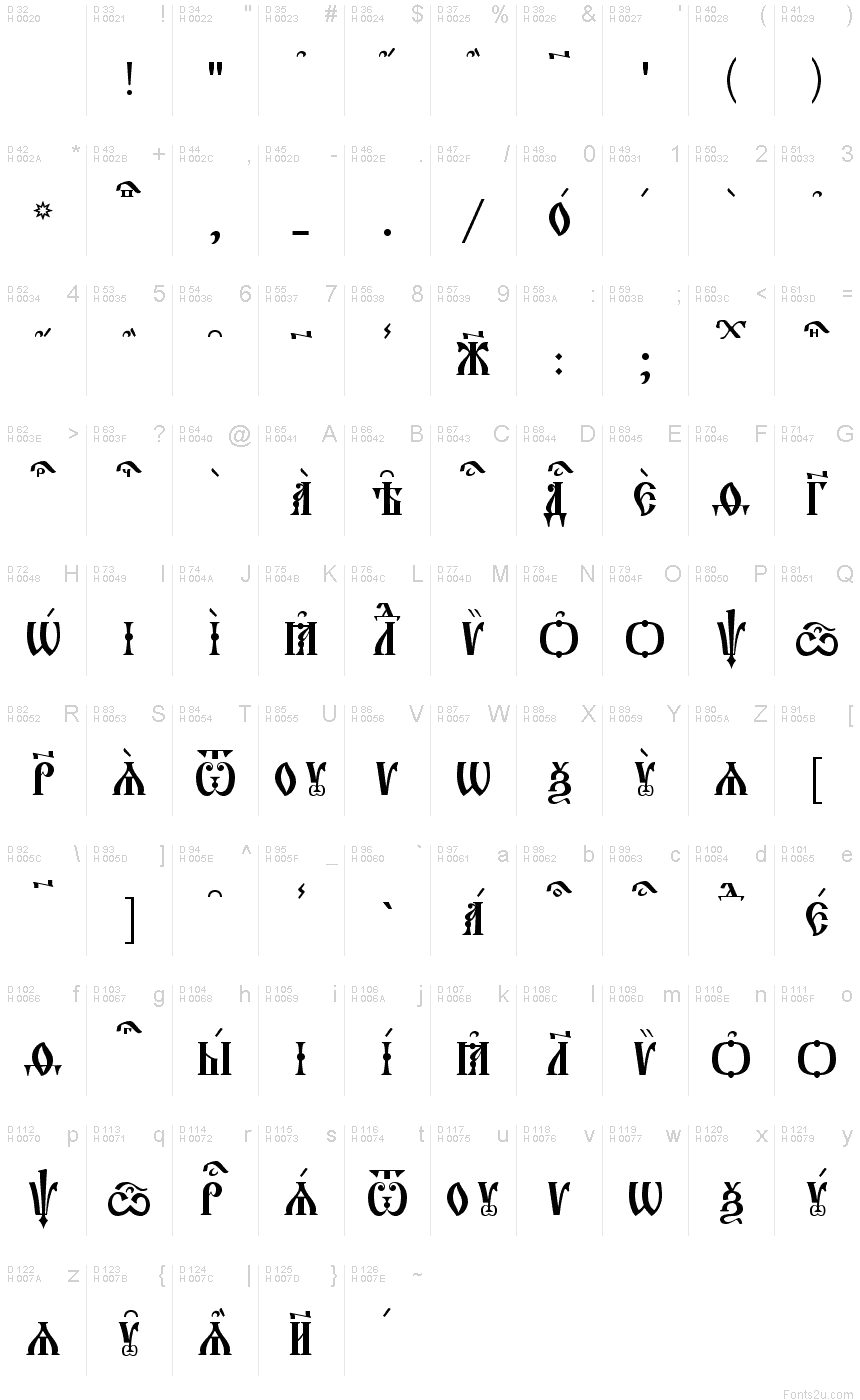
Orthodox TT UCS8 Caps SpacedOut, creata da SoftUnion Ltd e N. Andrushchenko, è un font cirillico gratuito in maiuscolo che richiama lo stile delle iscrizioni ecclesiastiche e delle antiche pagine liturgiche. Le lettere uniscono silhouette ampie e cerimoniali a piccoli dettagli a goccia, riccioli interni e accenti a forma di croce, rendendo il carattere solenne ma al contempo decorativo.
È perfetto per locandine di musica sacra, copertine di libri di storia slava, grafica museale, titoli e monogrammi dove poche lettere riescono a trasmettere da sole quel tono devozionale. Essendo un font gratuito, è ideale soprattutto per brevi esposizioni, poiché le sue maiuscole spaziate, simili a icone, donano la solennità delle iscrizioni incise, discostandosi dal testo di uso quotidiano.